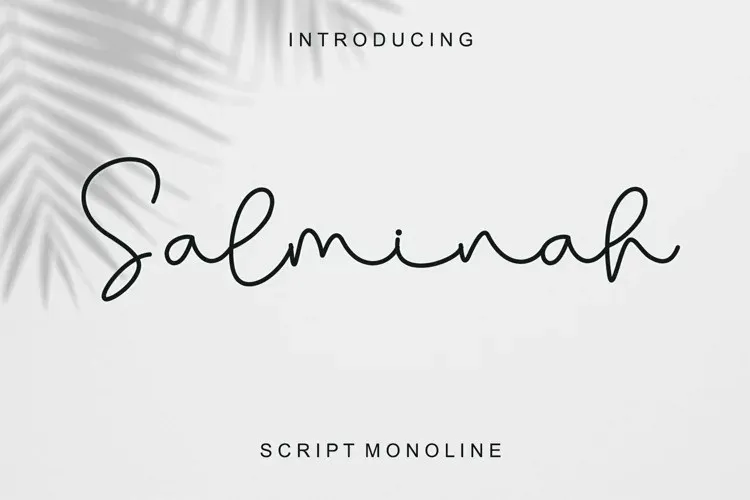
Salminah Font – Download Grátis
A Salminah Font é uma elegante tipografia script monoline criada por Ahmad Afandi. Com um estilo autêntico e casual, ela oferece letras fluídas que deixarão seu design com um toque único e aconchegante. Ideal para logos, cartões de agradecimento, desenhos em embalagens, identidades de marcas, projetos DIY, títulos de livros, convites de casamento, embalagens, e muito mais. Seja você um designer criativo ou iniciante no mundo dos projetos gráficos, a Salminah Font está aqui para tornar seus trabalhos ainda mais especializados.